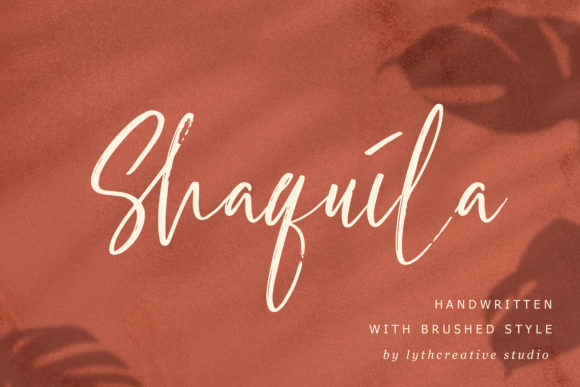
Creativefabrica Shaquila Font
[Creativefabrica] Shaquila Font
Шакила - это расслабленный и нежный рукописный шрифт. Этот универсальный скриптовый шрифт имеет широкий спектр применения, начиная от поздравительных открыток и заканчивая заголовками, и гарантированно добавит ослепительного ощущения вашему следующему проекту.